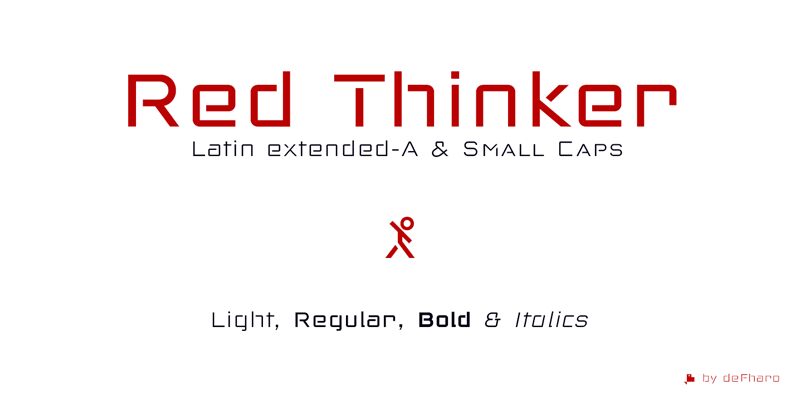
Red Thinker to bezszeryfowy krój pisma, który zawiera kapitaliki. Kwadratowe proporcje oraz połączenie miękkich krzywizn na zewnętrznych krawędziach z prostymi liniami wewnątrz znaków tworzą design typu semi-stencil, nadający mu technologiczny i futurystyczny charakter.
- Red Thinker to spadkobierca geometrycznych krojów pisma z początku XX wieku, inspirowany szkołą Bauhaus. Został zaprojektowany z myślą o uniwersalnym zastosowaniu w każdym rozmiarze, zarówno na ekranie, jak i w druku.
Red Thinker is a classic typeface versalitas sans serif of square proportion and rectilinear character with rounded poles and a semi-stencil design that gives it a futuristic and sci-fi look. - Red Thinker is the right heiress of geometric fonts from the early 20th century inspired by the Bauhaus school and is specially designed for use in small sizes for screen and printing